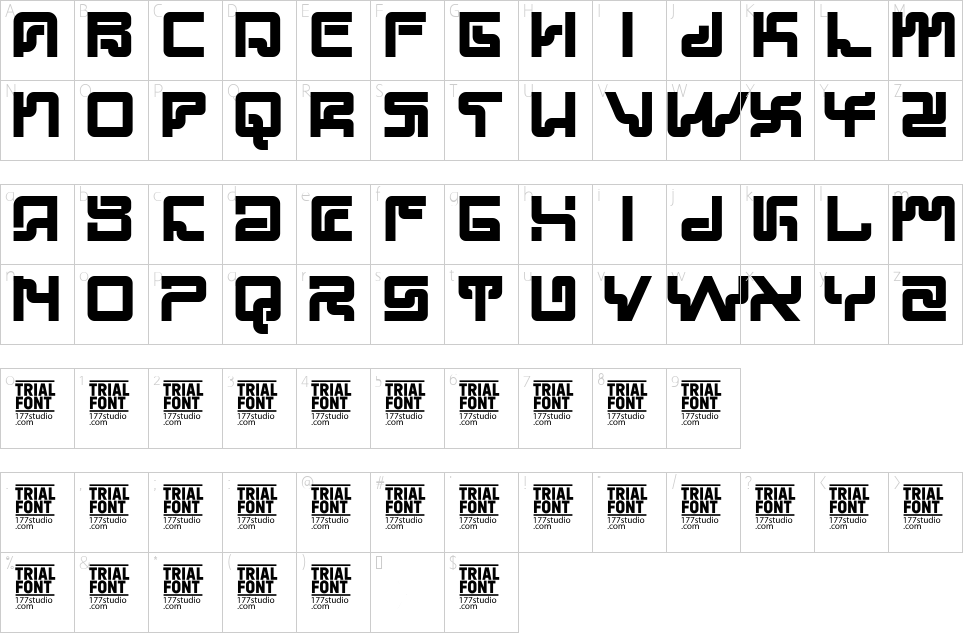
A fonte Science Existed é uma escolha ideal para qualquer projeto que exige um visual moderno e sofisticado. Desenvolvida pelo 177studio.com, esta fonte foi projetada para ajudar a criar gráficos, design de interfaces de usuário, e até mesmo títulos de livros de ciência. Com seu design moderno e elegante, ela oferece uma ótima solução para quem busca uma fonte de alta qualidade sem precisar investir em um projeto pago. Foi descarregada 261 vezes, o que nos dá uma indicação de que a qualidade da fonte é reconhecida por designers e profissionais de design. Se você busca uma fonte de alta qualidade sem investir em um projeto pago, a fonte Science Existed é uma excelente escolha.